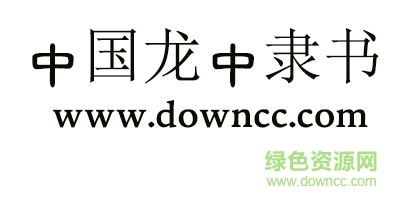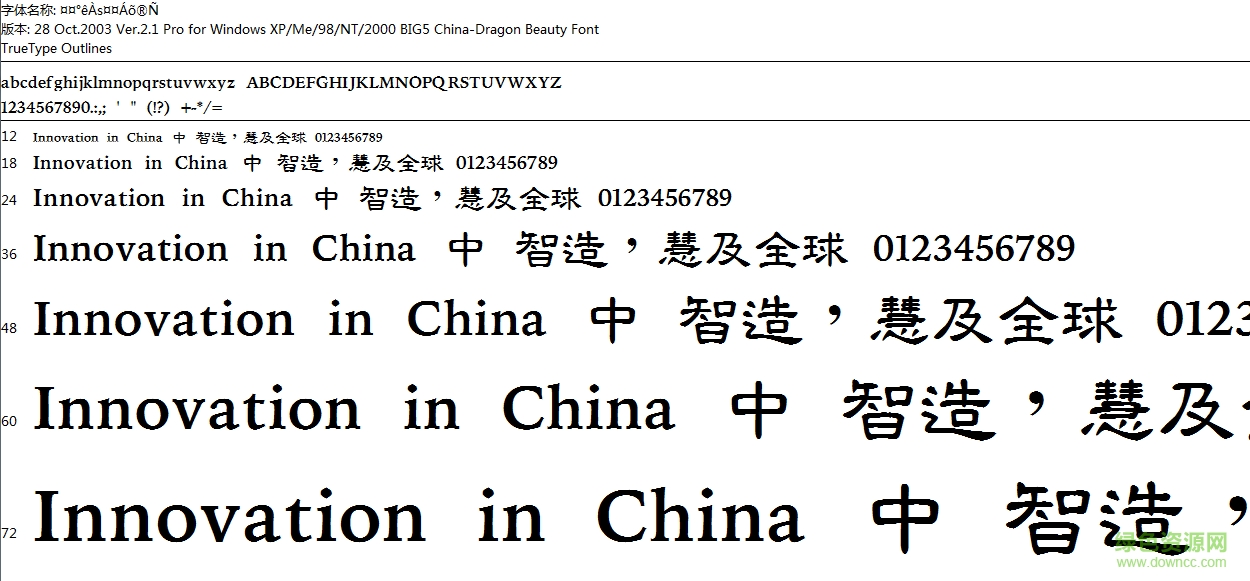
中國龍中隸書字體由中國龍字體庫推出!這款字體支持簡體繁文、英文以及阿拉伯?dāng)?shù)字輸入。具備了隸書體所有風(fēng)格特征。多用于印刷設(shè)計(jì)行業(yè)使用!歡迎下載安裝。
中國龍中隸書是一款中文繁體字體,這款字體線條流暢,字體效果略微寬扁,有需要的朋友歡迎來綠色資源網(wǎng)下載體驗(yàn)!